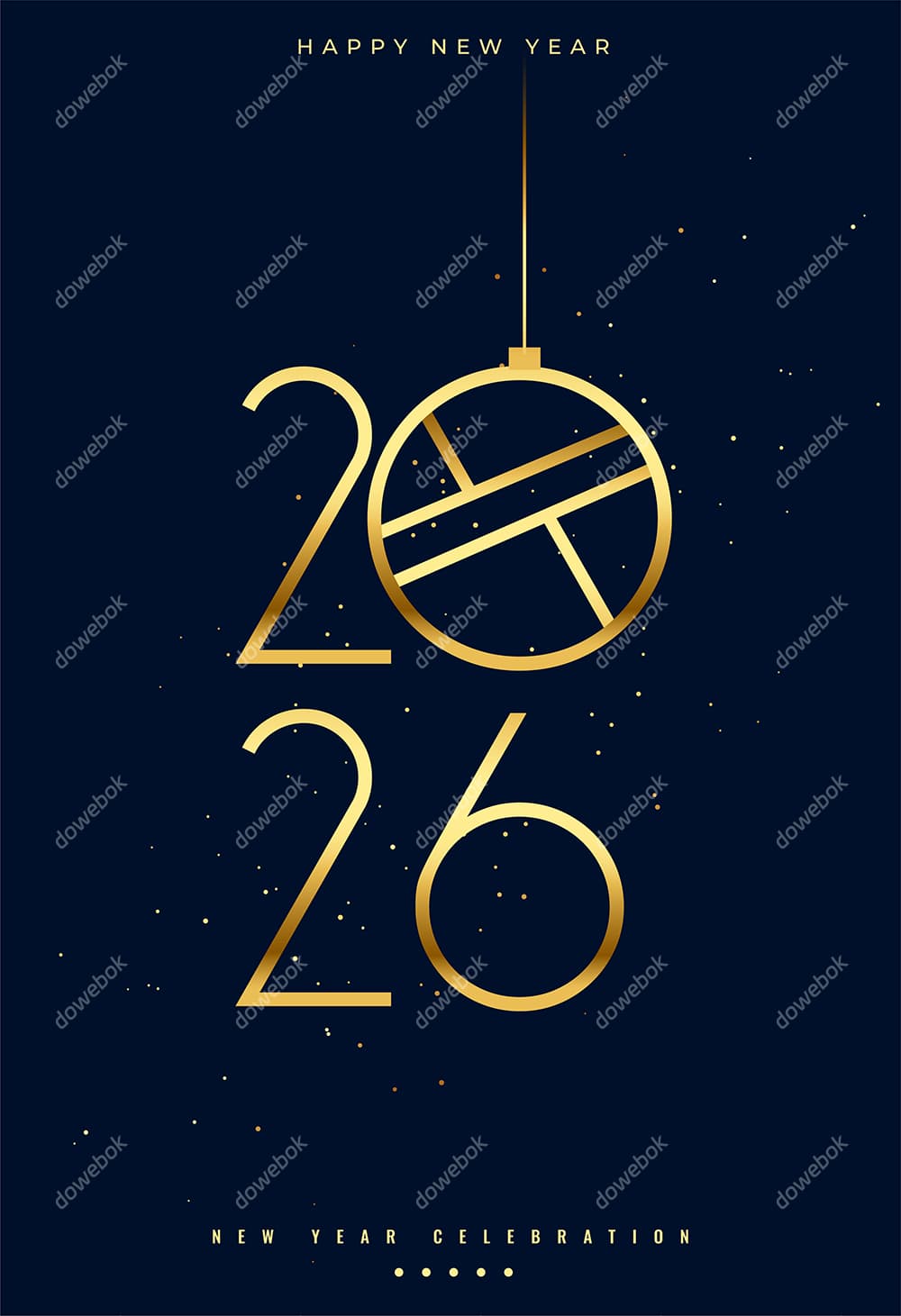
这是一款金色装饰球和数字设计的 2026 新年快乐矢量素材,深幽藏蓝背景缀着细碎金星光斑,鎏金 “2026” 字体将 “0” 化作悬挂的装饰球造型,线条简约精致。上下 “Happy New Year”“NEW YEAR CELEBRATION” 字样呼应主题,整体以蓝金配色融合节日挂饰元素,既显跨年的轻奢格调,又用星光细节烘托出温馨的仪式感,简洁中透出雅致的节日氛围。